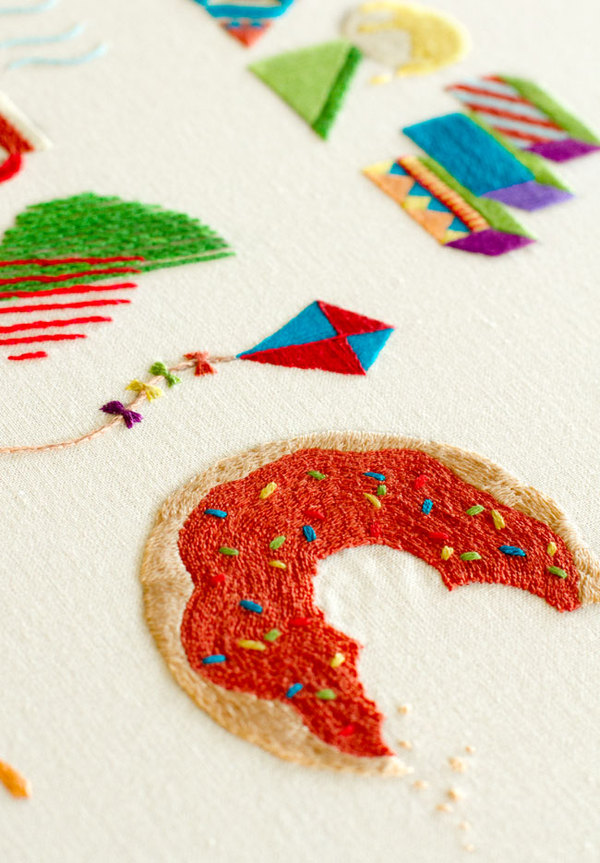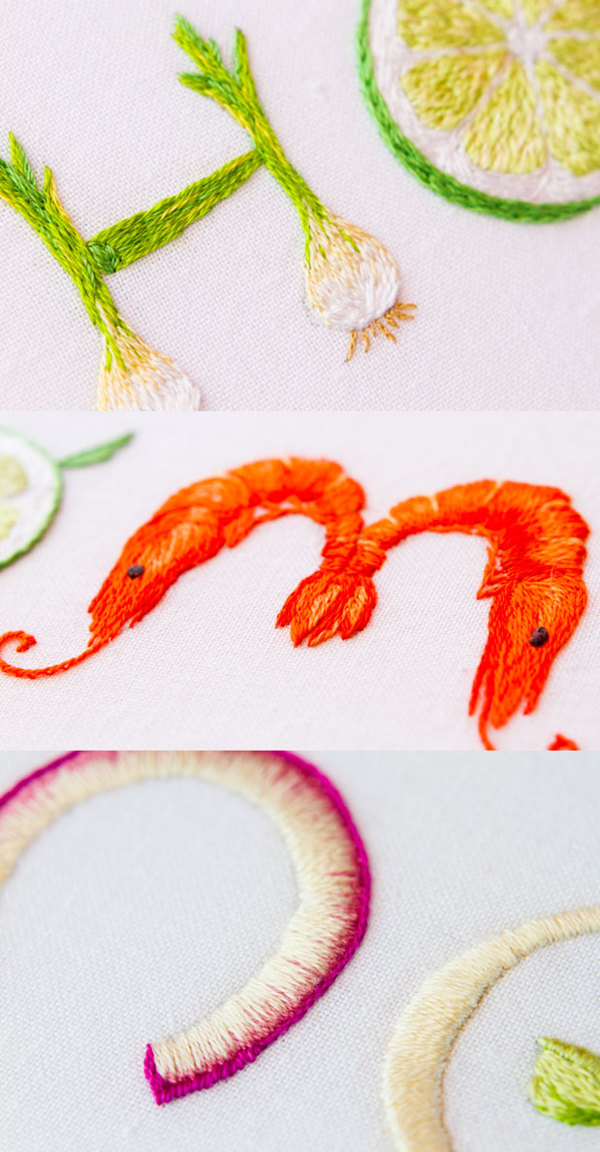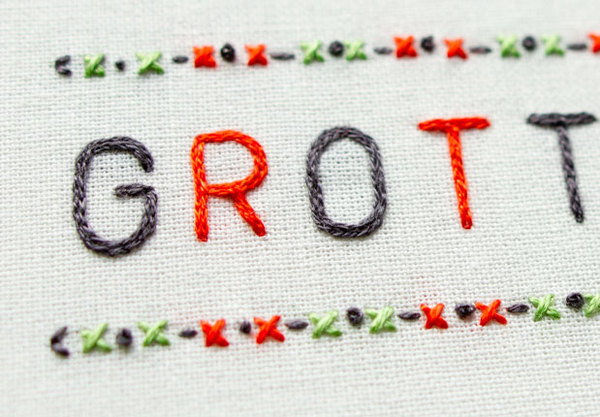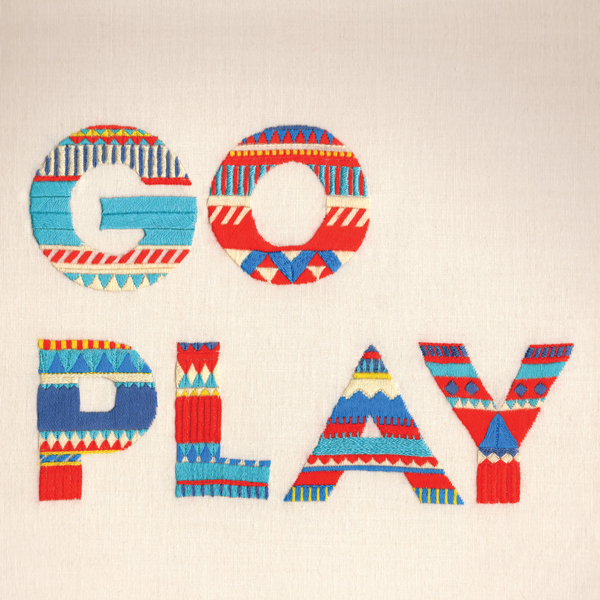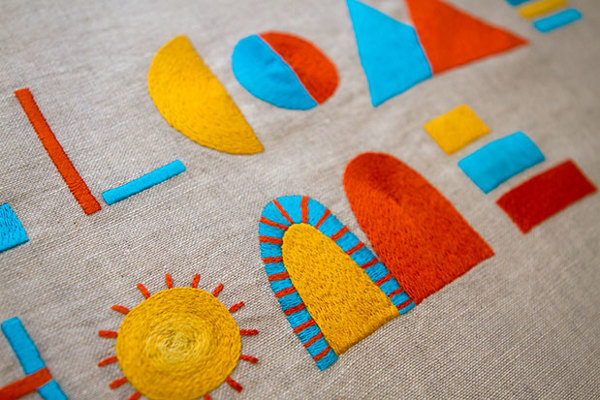
当手工刺绣遇到字体设计和插画
导语新浪微博:@尖峰视界澳大利亚悉尼的创意工作室MaricorMaricar Studio善于将手工刺绣艺术与字体/插画设计相结合,他们的作品色彩明快、设计精良,手工刺绣的工艺感更是令人着迷~
澳大利亚悉尼的创意工作室MaricorMaricar Studio善于将手工刺绣艺术与字体/插画设计相结合,他们的作品色彩明快、设计精良,手工刺绣的工艺感更是令人着迷~